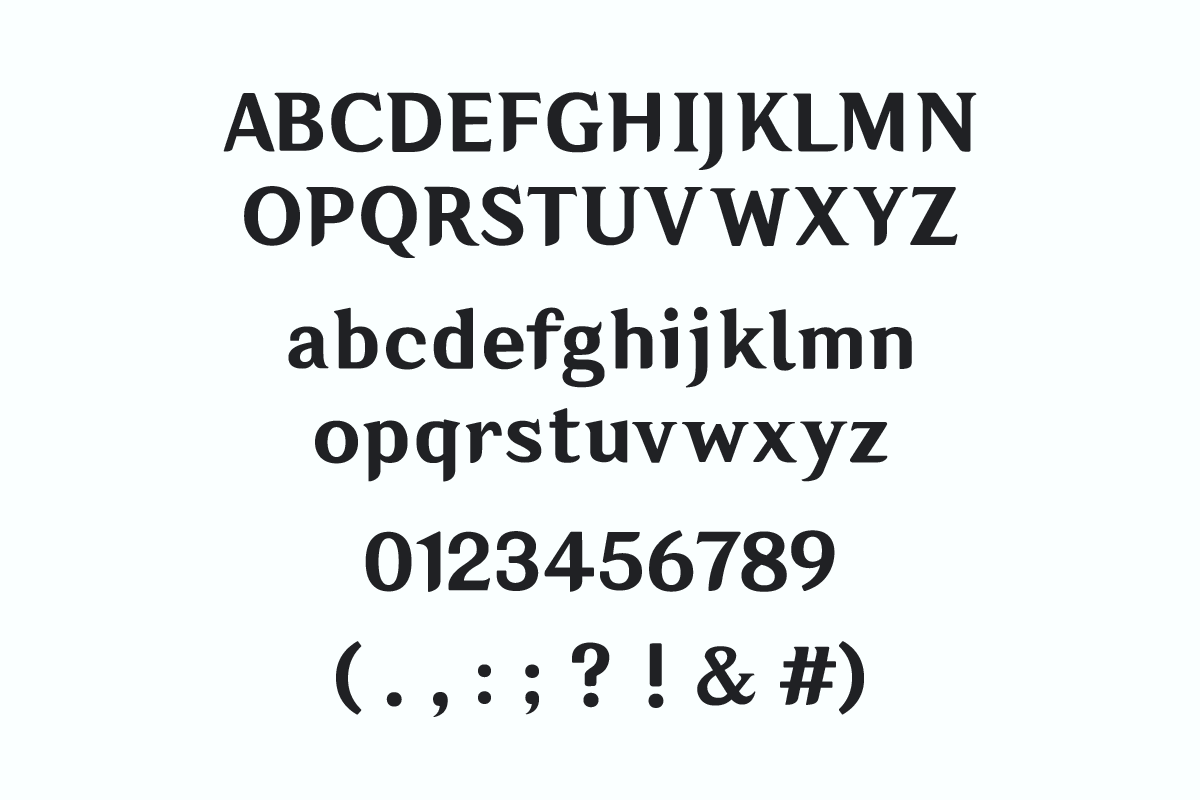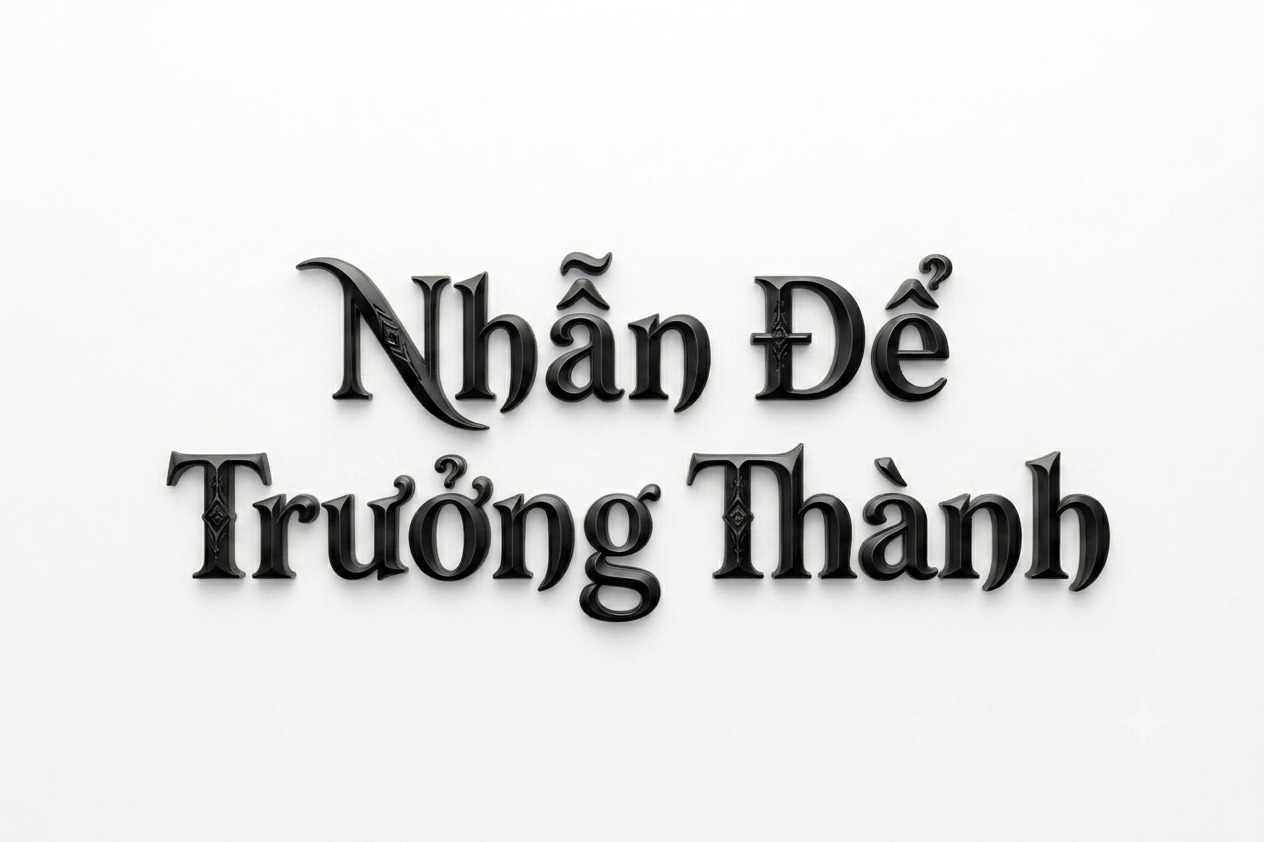
Genshin Impact Font gây ấn tượng với phong cách fantasy đặc trưng, kết hợp giữa nét chữ mềm mại, cổ điển và cảm giác phiêu lưu lấy cảm hứng từ thế giới giả tưởng. Tuy nhiên, nhiều phiên bản font trên Internet chưa được Việt hóa hoàn chỉnh, dễ gặp lỗi thiếu dấu, sai ký tự hoặc không đồng nhất khi đưa vào thiết kế.
Font Genshin Impact là gì?
Font Genshin Impact (thường được biết đến với tên gốc là HYWenHei-85W cho bản tiếng Trung hoặc các biến thể dựa trên phông chữ Latinh trong game) là linh hồn hình ảnh của tựa game nhập vai thế giới mở đình đám từ HoYoverse. Đặc trưng của bộ phông này là sự kết hợp giữa dòng Sans-serif hiện đại, vững chãi với các đường nét tinh tế, sắc sảo, gợi lên cảm giác phiêu lưu và kỳ ảo. Đây là lựa chọn hàng đầu cho các thiết kế tiêu đề poster sự kiện, bao bì hộp quà lưu niệm, in ấn thẻ nhân vật hoặc các vật phẩm merchandise dành riêng cho cộng đồng game thủ.
Tuy nhiên, phông chữ gốc thường gặp rào cản lớn về ngôn ngữ khi không hỗ trợ các dấu thanh đặc thù của tiếng Việt. Bản geshin impact việt hoá chuẩn tại In Viva đã được xử lý kỹ lưỡng từng ký tự “đ, ư, ơ” và các dấu mũ, đảm bảo Kerning (khoảng cách chữ) cân đối tuyệt đối. Việc sở hữu bản font genshin impact việt hóa chuẩn giúp các dự án của bạn không chỉ đúng tinh thần nguyên tác mà còn đạt độ thẩm mỹ cao khi thực hiện in ấn thực tế trên mọi chất liệu.
Lưu ý: Với geshin impact việt hoá, bạn nên kết hợp phông chữ này cùng các bảng màu đặc trưng của các nguyên tố (như màu xanh của Phong, màu vàng của Nham) để tăng hiệu ứng thị giác và nhận diện đúng tinh thần của game.